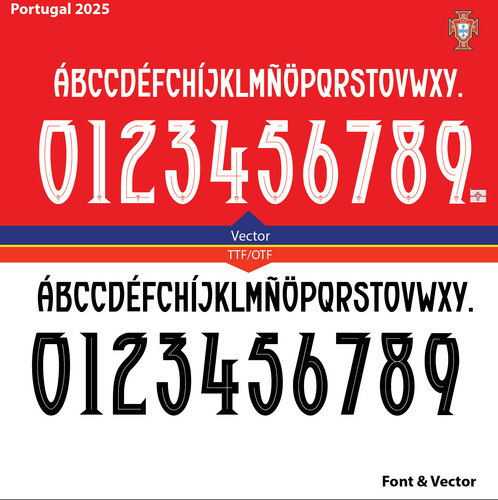
Presentamos la tipografía Portugal 2025, un recurso digital diseñado por Portal Studio que transformará tus proyectos creativos. Este archivo en formatos PDF, TTF y EPS es ideal para diseñadores gráficos, ilustradores y cualquier profesional que busque añadir un toque distintivo a su trabajo.
La tipografía Portugal 2025 no solo es visualmente atractiva, sino que también ofrece versatilidad en su aplicación, desde branding hasta diseño editorial. Su estilo único y contemporáneo hará que tus diseños se destaquen, capturando la atención de tu audiencia y mejorando la comunicación visual de tus proyectos.